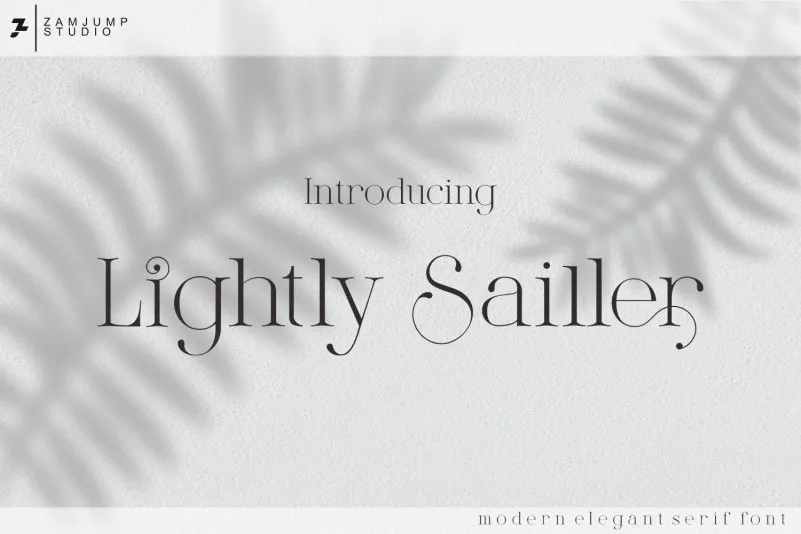
A Lightly Sailler Font é uma tipografia serif que transmite elegância sem perder simplicidade. Inspirada nas formas geométricas e os detalhes curvos orgânicos, esta fonte oferece um toque moderno ao mesmo tempo que mantém um charme nostálgico. Suas linhas suaves e afiadas criam um contraponto perfeito entre elegância e nostalgia, tornando-a uma escolha ideal para ambos o título e o texto de corpo da sua página. Além disso, a Lightly Sailler Font foi projetada com quatro ligaturas especiais (ct, st, it, ck), assim como alternativas tanto em letras maiúsculas quanto minúsculas que contêm um pequeno acréscimo na extremidade das letras. Este conceito permite criar um aspecto ainda mais elegante e dar destaque à sua composição de texto. Esta fonte é uma excelente opção para quem procura um equilíbrio entre estética moderna e nostalgia, capaz de se destacar em qualquer projeto gráfico que você possa estar desenvolvendo. Ideal tanto para aplicações no nível do título quanto para o conteúdo de corpo da página, a Lightly Sailler Font não apenas garante legibilidade, mas também um toque sofisticado e criativo ao usar seu design único.